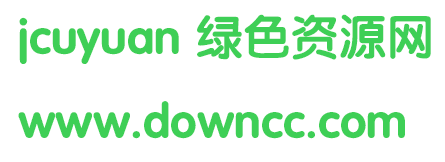
jcuyuan是什么字體?jcu yuan字體又叫迷你簡粗圓,粗粗圓圓的,稚拙有神,十分可愛,可用作卡通出版物印刷字體或海報(bào)設(shè)計(jì)字體,也是在生活中的宣傳廣告上比較常見的一種類型,喜歡的朋友快來綠色資源網(wǎng)下載吧!
圓體字體介紹
中文圓體指一種由黑體演變而來的字體。大概出現(xiàn)于清末。拐角處、筆畫末端為圓弧狀。字體清晰、端正、嚴(yán)肅,適合于報(bào)紙大字頭、圖書封面、招牌、廣告、網(wǎng)站標(biāo)題的制作。變體為幼圓體、琥珀體等。
英文圓體介紹
國內(nèi)常指代的圓體英文書法包括有 手寫印刷體、意大利體(或者意大利斜體、斜體)、圓體(國產(chǎn)圓體)